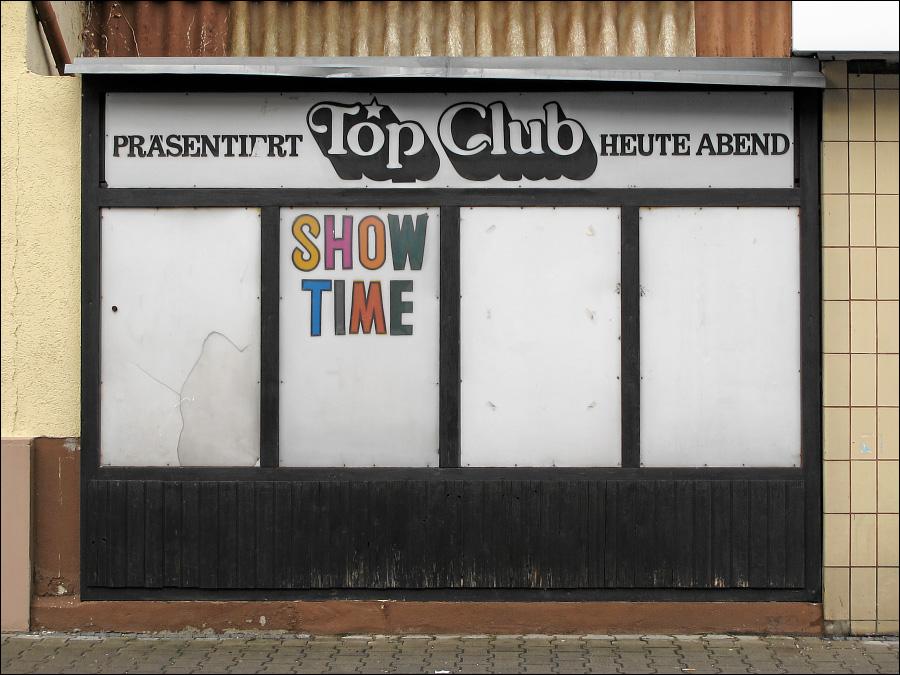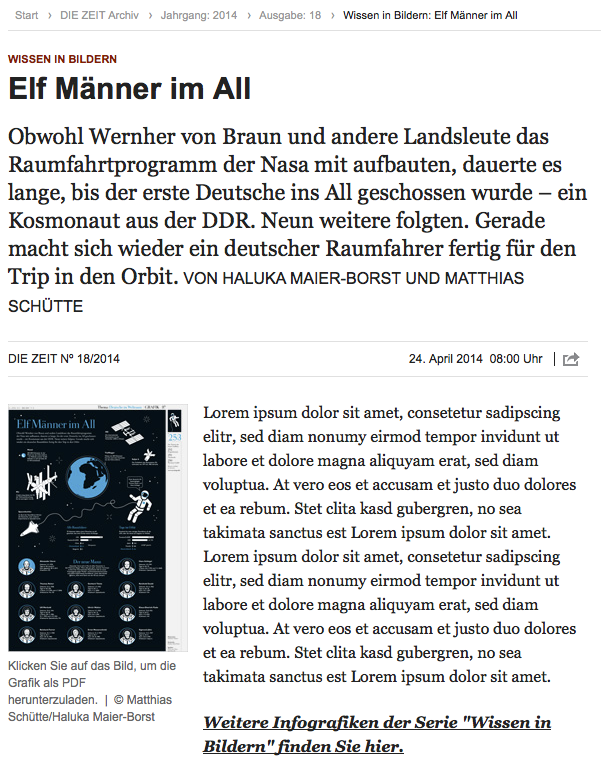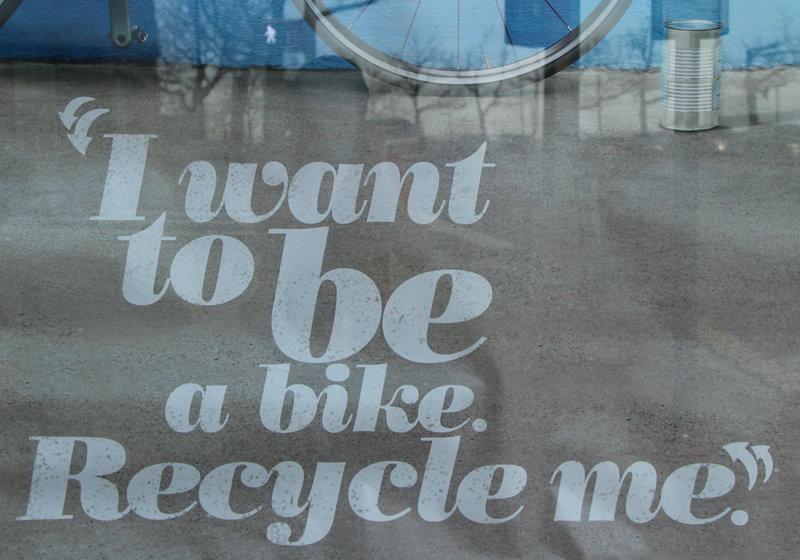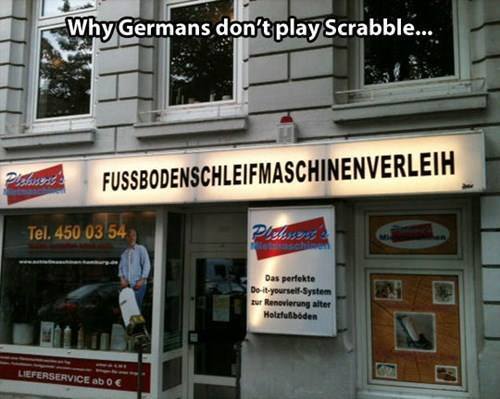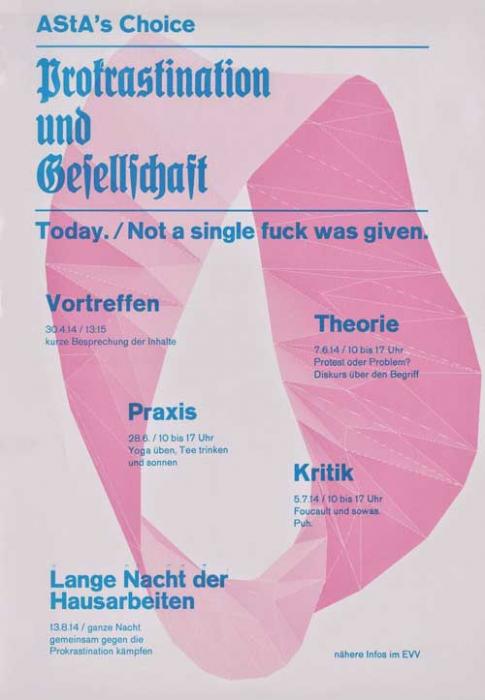
David Thorne again ...
If for some reason I do decide to use any of the existing graphic components, a quick search on Google for 'clipart of man holding clipboard' and 'blue wiggly line for no apparent reason' should suffice.
Vielleicht nicht im streben Sinne ein rein typografisches Fundstück, aber es kommen auch schöne Buchstaben darin vor und mich hat das Video gefreut :-)
Kann mal jemand Herrn Barilla sagen, dass das auch mit Macaroni geht ;-)
Na ja, man kann Propaganda noch so nett aussehen lassen, sie wird doch immer noch nach Propaganda riechen. Mehrere Meilen gegen den Wind.
Oh, mal wieder auf Thread-Schließungs-Mission?
Kann mal jemand Herrn Barilla sagen, dass das auch mit Macaroni geht ;-)
Die passen nur so schlecht in den Drucker, um die Unterstützungsnachrichten aufzudrucken. Vielleicht sollte man die dann eher lasern?
In Rüsselsheim:
Vermutlich aus den Siebzigern, aber noch heute zu bewundern.
Hatten wir das schon?
Nicht auf Youtube, aber dafür immer wieder in echt. Mit dem kleinen Unterschied, dass IRL die »Experten« meist auf der Seite der Auftraggeber sitzen und wir nur die monkeys sind, die das mal eben schnell ausführen sollen.
Fehlen nur noch ein paar weit klaffende Löcher zwischen Text und Anführungen: « Falsch angeführt » – zehn Typographen und Korrektoren attackieren Bild.
Wir reden hier von der BILD. Da darfst du nicht erwarten, dass sie es richtig falsch machen.
Plakat des AStA der HBK Braunschweig
Bei der Headline-Schrift handelt es sich
um die schmalfette König-Type von Heinz König,
Schriftgießerei Emil Gursch, Berlin, um 1906.
Wenn eh kein Mensch mehr Texte ließt, kann man auch das Schreiben der selben lassen. So etwa dachte sich die Zeit das hier wohl :hammer:
Warum Deutsche kein Scrabble spielen?
Weil’s beim Scrabble kein ẞ gibt  :nicken: .
(Erstaunlich finde ich ja das korrekt durchgekoppelte Do-it-yourself-System.)
Den Betrieb gibt es seit 1957. Damals™ hat man das noch richtig in der Schule gelernt. Wahrscheinlich sogar in Hamburg.
Was ist denn mit dem R passiert ..?
Oder es hat sich das Bein gebrochen – man sollte das gipsen :hammer: